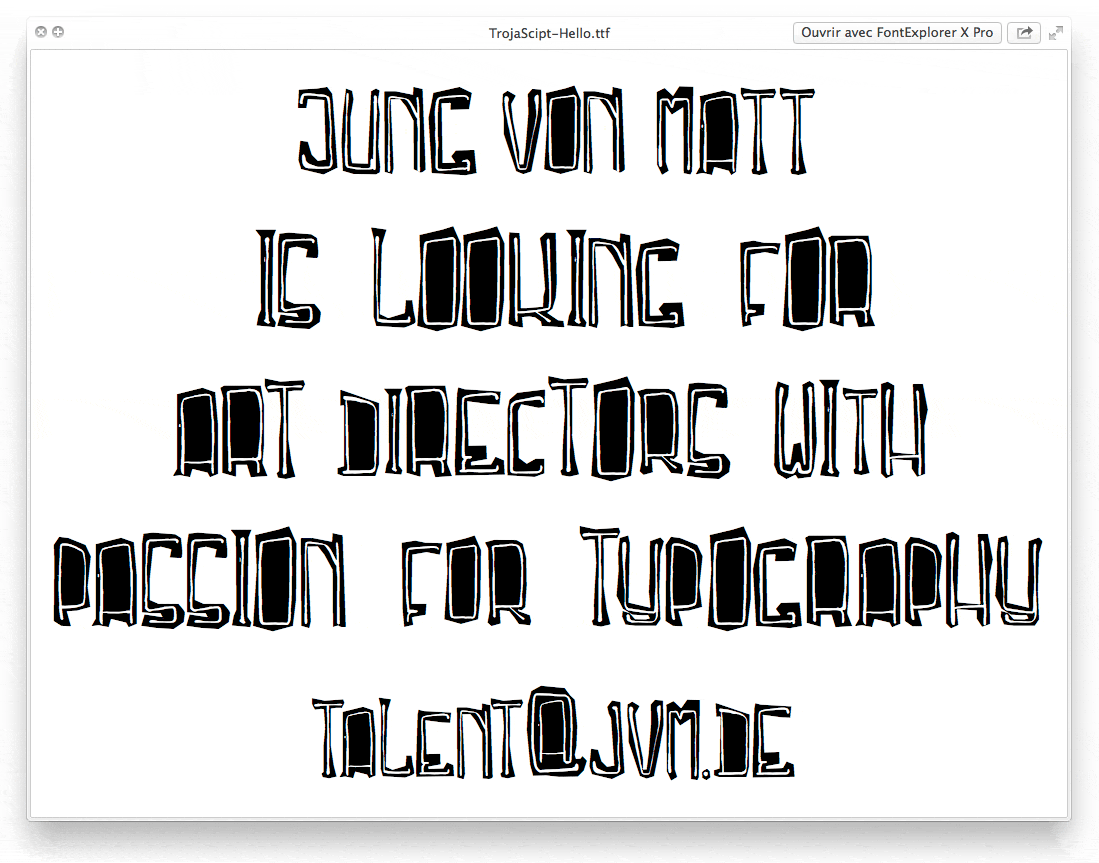
Voici comment l'agence de publicité allemande Jung Von Matt a recruté "Paul", un designer graphique fan de typographie.
Pour découvrir l'annonce, il fallait un talent de Sherlock-Holmes, une bonne dose de chance et un goût affirmé (ou presque !)pour la typographie !
Le procédé est simple et astucieux.
Ils ont commencé par créer une typographie, qu'ils ont proposés en téléchargement gratuit sur les de nombreux sites de typographies (exemple). Cette police dénommée 'Troja Script' a été téléchargée pas moins de 14 000 fois et recelait en réalité une offre d'emploi cachée.
Ils avaient simplement modifié l'ordre des lettres de sorte qu'en visualisant un aperçu de la typo, l'annonce apparaissait !
23 petits malins se sont donc rapprochés de Jung Von Matt pour postuler au poste de designer. C'est 'Paul' qui a finalement été recruté. Son premier job fut probablement de raconter cette histoire dans ce clip !
Après, à la vue de la typo, qui plus est trouvée sur un site comme dafont, on peut sérieusement mettre en doute les compétences réelles de 'Paul' !